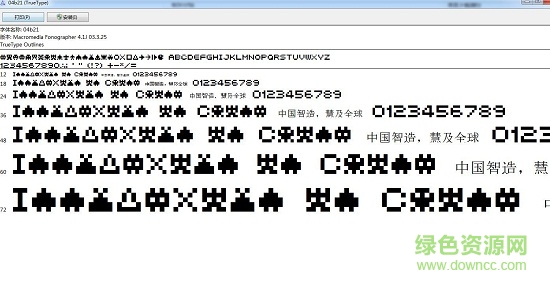
04b 21-普通
04b21是什么字體?04b 21字體是一款普通的像素字體,這款字體風(fēng)格大膽,清晰度非常高,縮小了依然能夠正常瀏覽,適用于品牌廣告或是視覺(jué)設(shè)計(jì)方面,有需要者歡迎在綠色資源網(wǎng)下載!
04b21字體特點(diǎn)
具有強(qiáng)烈的時(shí)代氣息,適用于LED屏等電子屏幕,在易識(shí)的同時(shí),體現(xiàn)科技感和現(xiàn)代感。
04b21字體